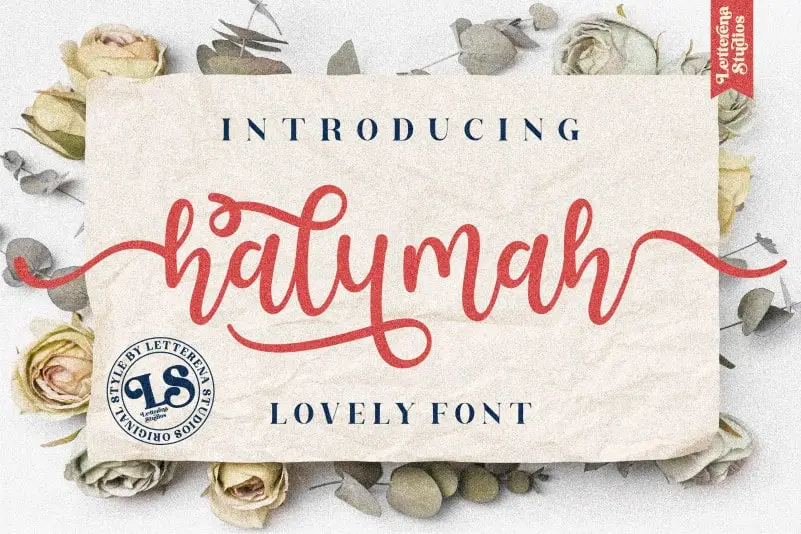
Halymah Calligraphy Font – Download Grátis
A Halymah Calligraphy Font é uma fonte escrita a mão única com uma aparência digna de atenção, sofisticada e eterna. Perfeita para aqueles que valorizam um toque pessoal em suas criações gráficas, esta fonte se destaca quando usada em convites de casamento, cartas de agradecimento, citações, cartões de felicitação, logotipos e mesmo nas cartelas empresariais. O PUA Encoding garantido pela fonte permite que você facilmente accione todas as letras e traços finais, tornando o processo criativo ainda mais dinâmico. Uma opção única para adicionar um toque especial a qualquer design de escrita a mão.